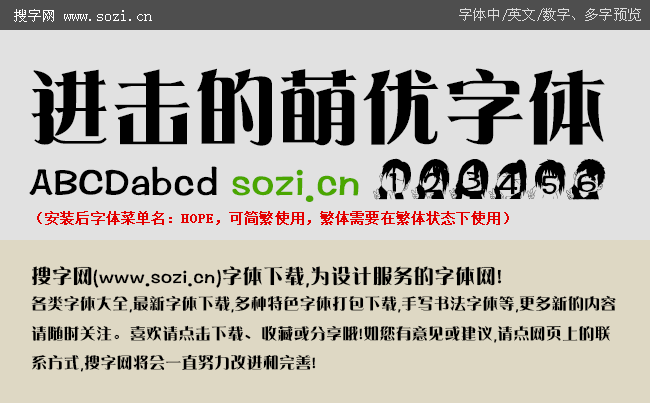
進(jìn)擊的萌優(yōu)字體
搜字網(wǎng)給大家提供一款藝術(shù)風(fēng)格的手機(jī)中文字體下載。字體名字叫進(jìn)擊的萌優(yōu)字體,這款手機(jī)字體是以華康雅宋體字體為原形。數(shù)字部分加上了漂亮的卡通外框,華康雅宋體以宋體的基礎(chǔ)上加以美化,比劃處修以花邊,轉(zhuǎn)折處稍微圓潤(rùn),相比棱角分明的宋體,又多了一分可親近的感覺(jué)。該字體端正大方,且結(jié)構(gòu)清晰、風(fēng)格統(tǒng)一,特別適合喜歡手機(jī)字體個(gè)性一些的朋友在手機(jī)上安裝使用。